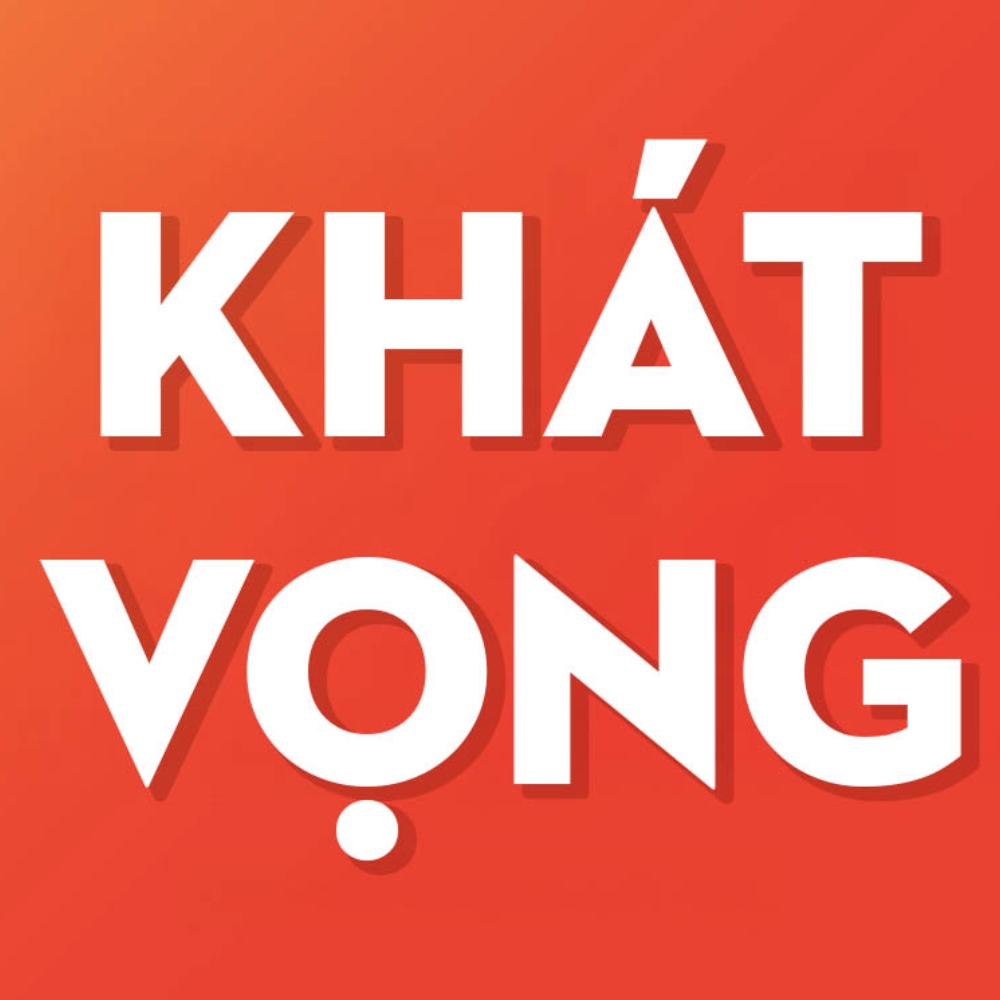
Tải font SVN là lựa chọn phổ biến tại Việt Nam với bộ font đa dạng, được Việt hóa từ nhiều kiểu chữ nổi tiếng trên thế giới. Nhờ hỗ trợ tiếng Việt đầy đủ và phong cách phong phú, font SVN được ứng dụng rộng rãi trong thiết kế bao bì, túi giấy, catalogue và các ấn phẩm in ấn thương mại.
Ở bài viết này, In Viva giới thiệu download font svn với các phiên bản phổ biến nhất bao gồm tải font svn gilroy, tải font svn gotham, download font gilroy và tải font svn yipes cùng các font thay thế miễn phí hợp pháp.
Bộ font SVN là gì?
Bộ font SVN (SVN Fonts Vietnam) là bộ font chữ được việt hóa từ các font nổi tiếng thế giới. SVN ra đời với mục đích giúp designer Việt Nam dễ dàng sử dụng các font đẹp mà không lo lỗi hiển thị tiếng Việt – vấn đề phổ biến khi dùng font gốc chưa hỗ trợ dấu thanh.
Bộ font SVN bao gồm hàng trăm font được việt hóa từ các font gốc nổi tiếng như Gilroy (thành SVN Gilroy), Gotham (thành SVN Gotham), Avo (thành SVN Avo), Brandon Grotesque (thành SVN Brandon), và nhiều font khác. Mỗi font SVN thường có từ 2-8 phiên bản với độ dày khác nhau (Thin, Light, Regular, Medium, Bold, Black).
Các font SVN phổ biến nhất:
- SVN Gilroy: Việt hóa từ Gilroy – font geometric hiện đại, được yêu thích nhất trong bộ SVN.
- SVN Gotham: Việt hóa từ Gotham – font mạnh mẽ, đô thị của Obama campaign.
- SVN Avo: Việt hóa từ Avenir – font sans-serif thanh lịch, minimalist.
- SVN Yipes: Font độc đáo với phong cách vui nhộn, năng động.
- SVN Brandon Grotesque: Việt hóa từ Brandon Grotesque – font rounded geometric.
- SVN Proxima Nova: Việt hóa từ Proxima Nova – font geometric hiện đại.
- SVN Futura: Việt hóa từ Futura – font geometric cổ điển.
- SVN Poppins: Việt hóa từ Poppins – font geometric thân thiện.
Ưu điểm lớn nhất của font SVN là hỗ trợ đầy đủ tiếng Việt với tất cả dấu thanh (á, à, ả, ã, ạ, ă, ắ, ằ…), trong khi font gốc thường không hỗ trợ hoặc hỗ trợ kém.
Tải font SVN trọn bộ miễn phí
Bộ font SVN Việt hóa được ưa chuộng nhờ hiển thị tiếng Việt chuẩn, dễ đọc và đa dạng phong cách, phù hợp cho thiết kế và in ấn. Việc tải đầy đủ giúp bạn linh hoạt lựa chọn font cho từng mục đích sử dụng. Dưới đây là bảng tổng hợp tải font svn việt hóa phổ biến nhất:
Tên font SVN |
Font gốc | Phong cách |
Ứng dụng in ấn |
SVN Gilroy |
Gilroy | Geometric hiện đại, sạch sẽ. | Logo startup, bao bì công nghệ, thời trang. |
SVN Gotham |
Gotham | Geometric mạnh mẽ, đô thị. | Bao bì thời trang, poster, catalogue cao cấp. |
SVN Avo |
Avenir | Sans-serif thanh lịch, minimalist. | Bao bì mỹ phẩm, organic, lifestyle. |
SVN Yipes |
– | Vui nhộn, năng động, trẻ trung. | Bao bì trẻ em, đồ chơi, thực phẩm vui. |
SVN Brandon Grotesque |
Brandon Grotesque | Rounded geometric, thân thiện. | Logo cafe, bakery, bao bì thực phẩm. |
SVN Proxima Nova |
Proxima Nova | Geometric hiện đại, chuyên nghiệp. | Catalogue, brochure, túi giấy doanh nghiệp. |
Ứng dụng font SVN trong in ấn và thiết kế bao bì
Bộ font SVN với sự đa dạng được ưa chuộng trong thiết kế Việt Nam:
- Hỗ trợ tiếng Việt hoàn hảo: Lý do chính khiến SVN phổ biến – tất cả dấu thanh hiển thị chuẩn, không lỗi font.
- Đa dạng phong cách: Từ geometric hiện đại (SVN Gilroy, Gotham), thanh lịch (SVN Avo), đến vui nhộn (SVN Yipes) – có font cho mọi nhu cầu.
- Quen thuộc với designer Việt: Hầu hết designer Việt đều biết SVN, dễ trao đổi file.
- Dễ tìm kiếm: Font SVN dễ tìm và tải về, phù hợp startup có ngân sách hạn chế.
Font SVN xuất hiện trong nhiều sản phẩm in ấn:
- Bao bì sản phẩm đa ngành: công nghệ, thời trang, mỹ phẩm, thực phẩm.
- Túi giấy thương hiệu: túi kraft, túi couche in logo với SVN Gilroy, SVN Gotham.
- Catalogue, brochure: SVN Avo, SVN Proxima Nova chuyên nghiệp.
- Hộp quà tặng: SVN Gilroy Bold, SVN Gotham Black nổi bật.
- Nhãn sản phẩm: SVN Brandon, SVN Yipes dễ thương.
- Menu nhà hàng: SVN Avo thanh lịch, SVN Brandon thân thiện.
- Poster sự kiện: SVN Gilroy, SVN Gotham hiện đại.
- Name card: SVN Avo, SVN Proxima Nova chuyên nghiệp.